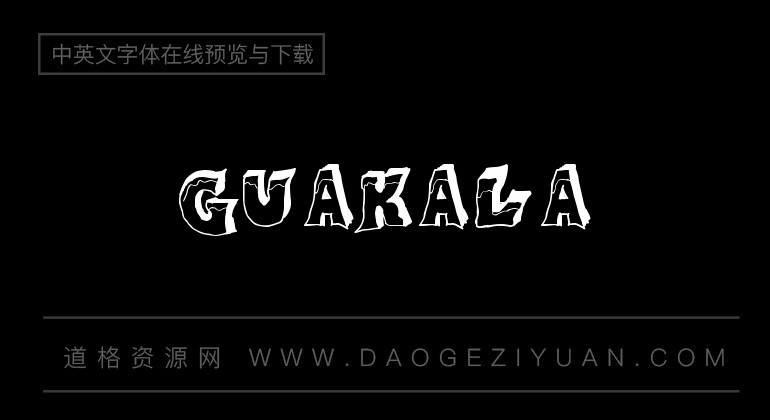
Guakala
Guakala是一种非常流行的字体,由Chilean Type设计师Rodrigo Araya Salas创建。这是一种手写风格的字体,非常适合用于海报、包装、广告、音乐封面等设计项目中。 这种字体具有浓郁的拉丁美洲味道,字母形状非常奇特,每个字母都带有一些装饰性的曲线和线条。 Guakala字体使用单一线宽度,但字母之间的间距和高度差异使其非常独特。 这种字体有五种类型,包括常规、粗体、斜体、粗斜体和轮廓,可满足不同类型的设计需求。无论是大幅海报、简单卡片,还是商标设计,Guakala都能够为您的设计增添生动、有趣的元素。
Guakala是一款非常不错的手写艺术字体,具有很好的视觉感,适合于文化类的宣传设计、商业类品牌的广告和产品包装设计以及个性化文字排版等较多场景。